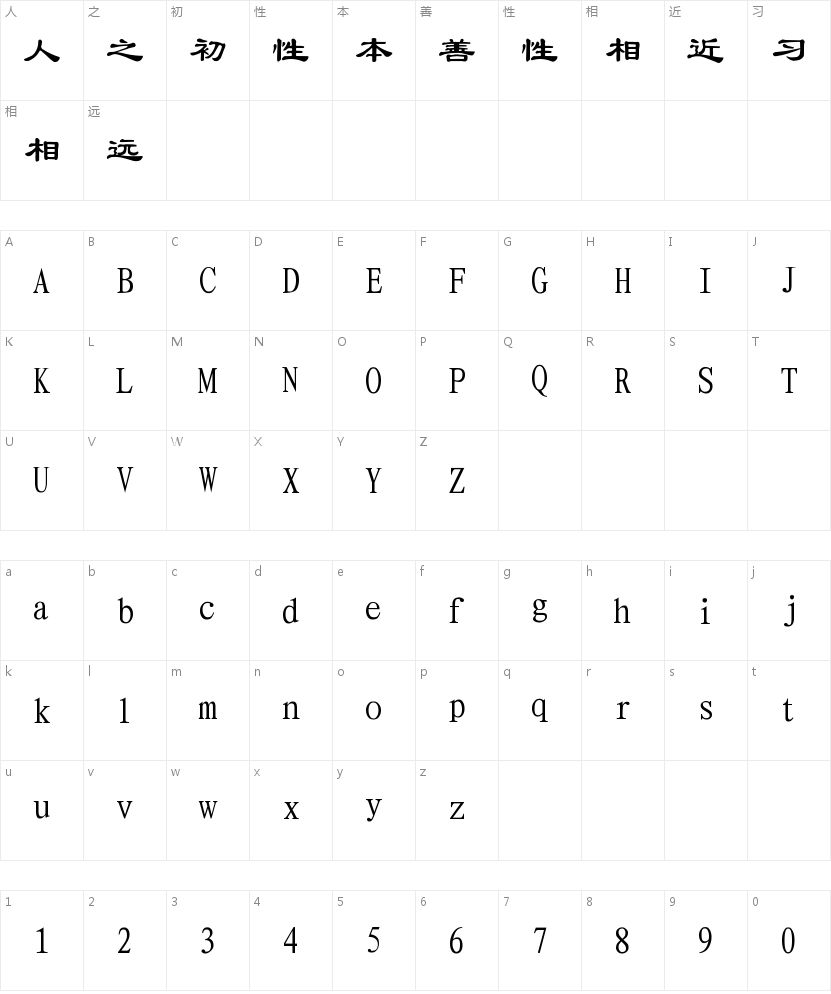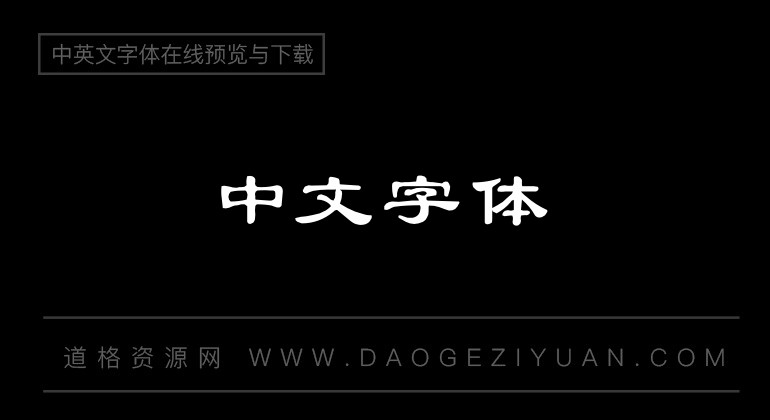
四通利方隶书体
四通利方隶书体(Simplified Li Style Official Script)是一种简化的中国隶书,它源于中国古典隶书,是由著名书法家李可染于20世纪初改编而成的。四通利方隶书体以简洁、结构紧凑、笔画清晰、挥洒自如的特点著称,是一种非常流行的书法字体,广泛应用于书法、绘画、纪念品等领域中。它的笔画精练,构图紧凑,笔势挥洒,笔画和线条组合灵活,能够表达出作者的内心感受,是一种具有艺术美感的书法字体。
四通利方隶书体是一款非常不错的手写艺术字体,具有很好的视觉感,适合于文化类的宣传设计、商业类品牌的广告和产品包装设计以及个性化文字排版等较多场景。